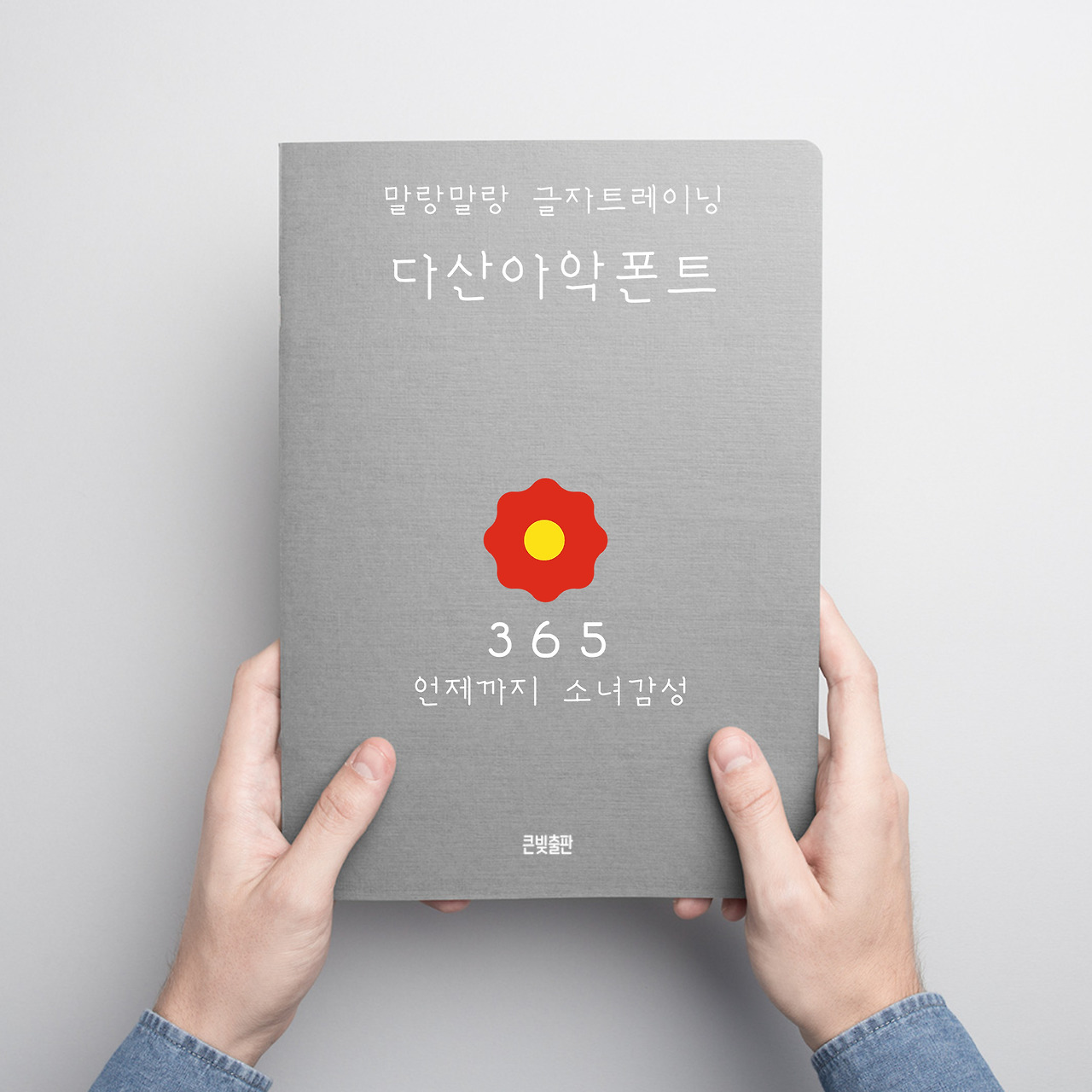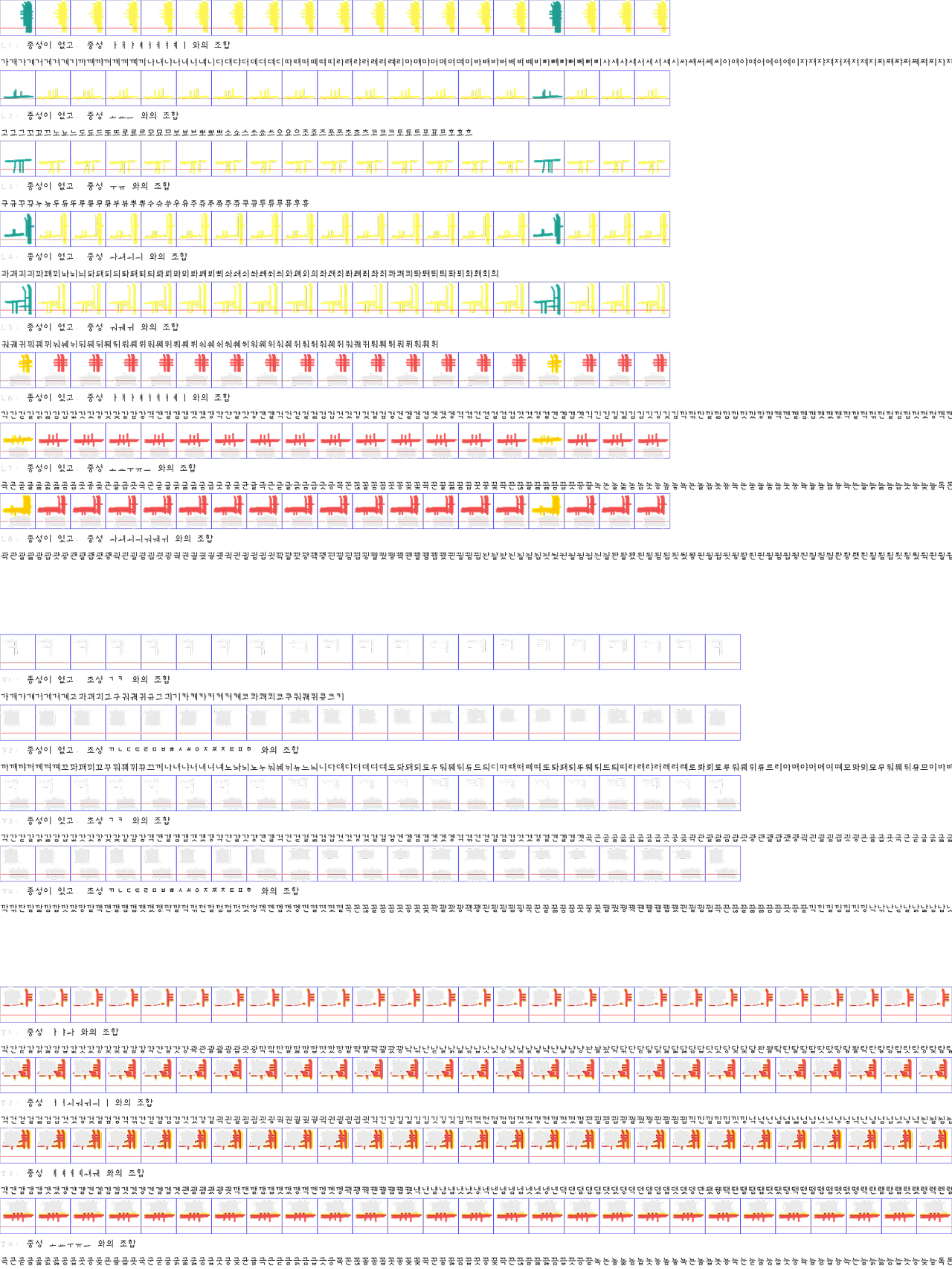
다산 정약용 아악체 폰트 만들기3
다산 정약용 선생의 어린이를 위한 외국어 학습서 아악편에 나온 글자를 폰트로 만들어봤습니다. 몇일 작업해서 최소한의 구성은 끝냈습니다. 한글날 배포할 정도까지 해보고 싶은데 가능할까요? 이제 글자 따라쓰기 노트로 본인의 레터링 작업 또는 손글씨를 폰트로 만들 사전준비는 거의 끝나가고 있습니다. 출판사의 IP인 표지 레터링과 같은 폰트를 생성하는 것이 가능해지는 것이죠.
그리고 전문 폰트 프로그램을 사용하지 않고 따로 개발해서 운영중입니다. 매트릭스 부분이나 다른 영문, 한글, 글자간 커닝을 맞추는 것은 AI를 도입해서 해결할 예정입니다.
또한 한글 따라쓰기용 유형을 제공하는 노트도 만드는 중입니다. 하단 조합으로 몇가지 글자유형의 가이드를 가지고 글자를 만들어가게 됩니다. 아날로그에 익숙한 분에게는 종이노트, 디지탈에 익숙한 분에게는 PDF파일이나 드로잉 웹으로 보면서 확인하실 수 있게 할 예정입니다. (현재는 폰트 완성도를 맞추기위해 몇가지 유형만 제공하나 도형으로 구분된 가이드폰트를 만드는 중입니다.)
아악체 폰트 만들기는 이제 거의 마무리가 되어 가는 것으로 저희 폰트의 특징은 스트로크로 만든 폰트이며 플로터, 레이저, 자수기, 로봇팔 같은 기계가 인식하기 쉬운 방식과 최소한의 움직임으로 설계 제작되었습니다.